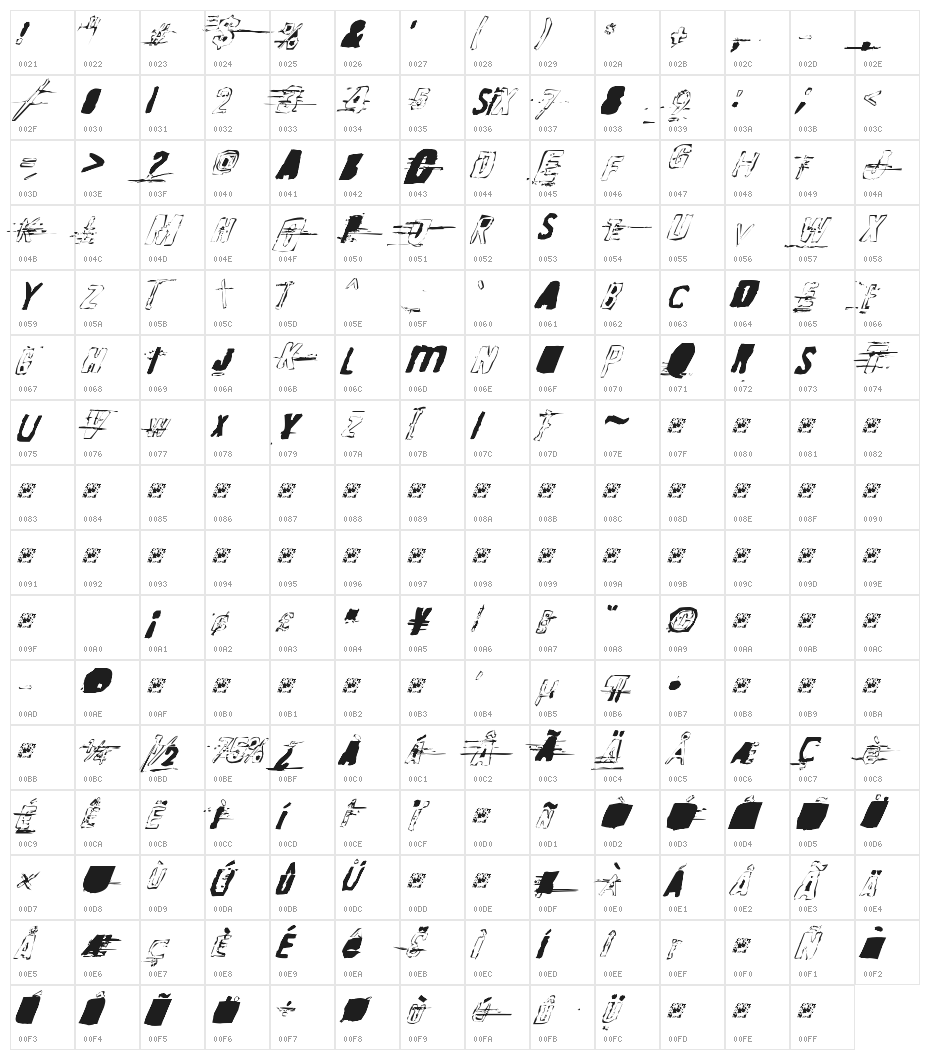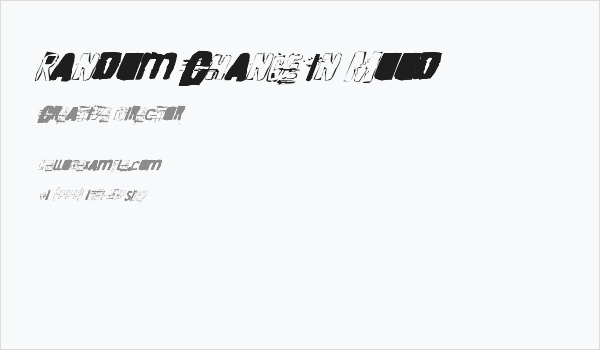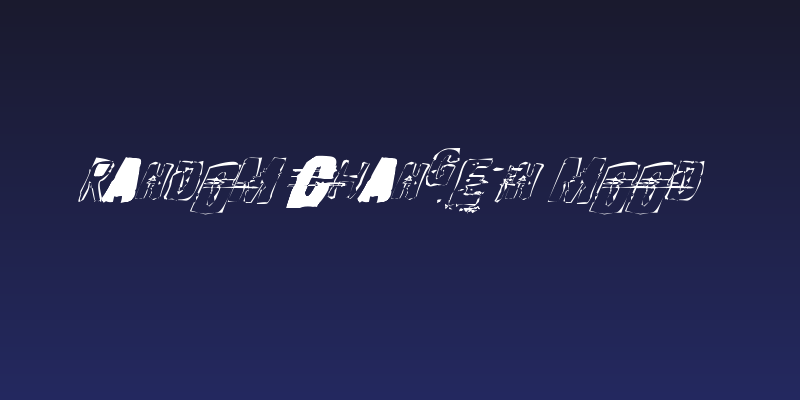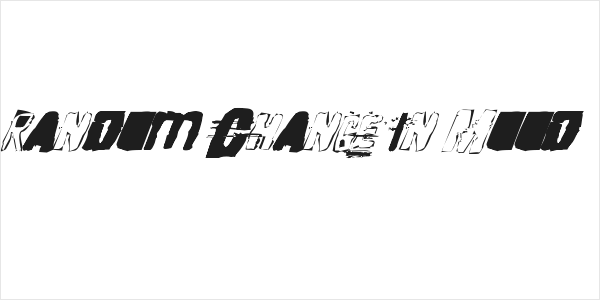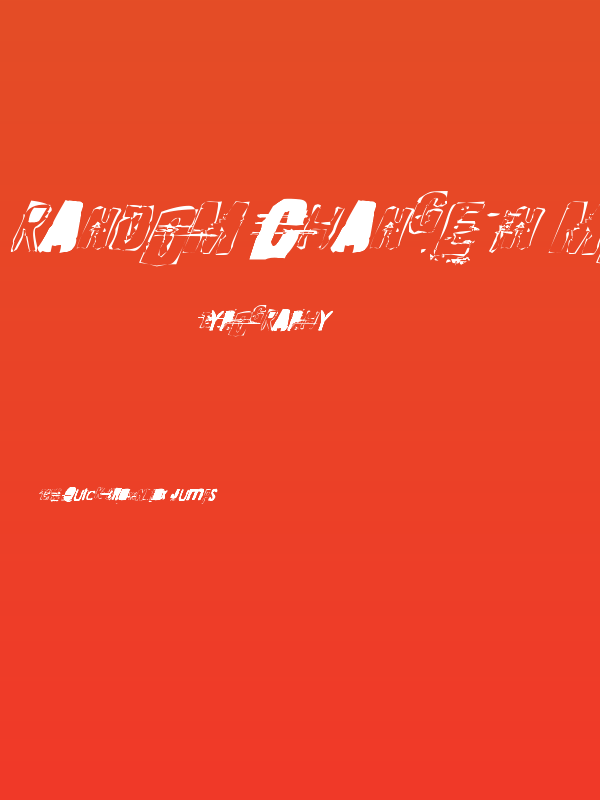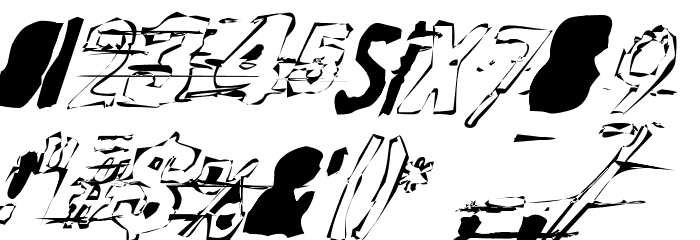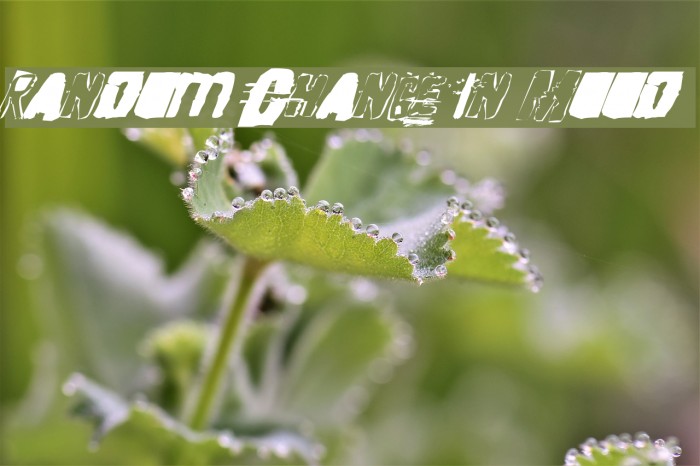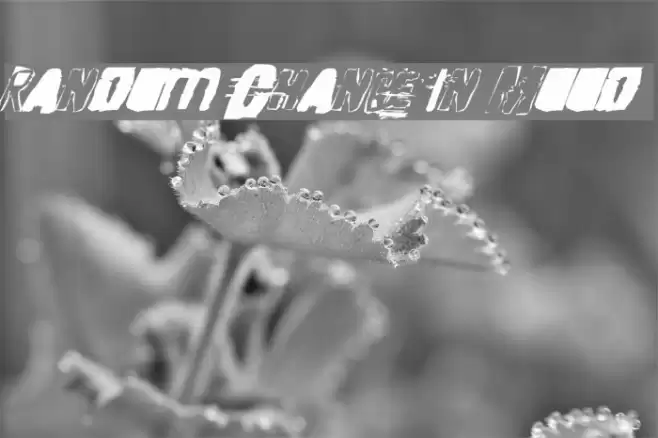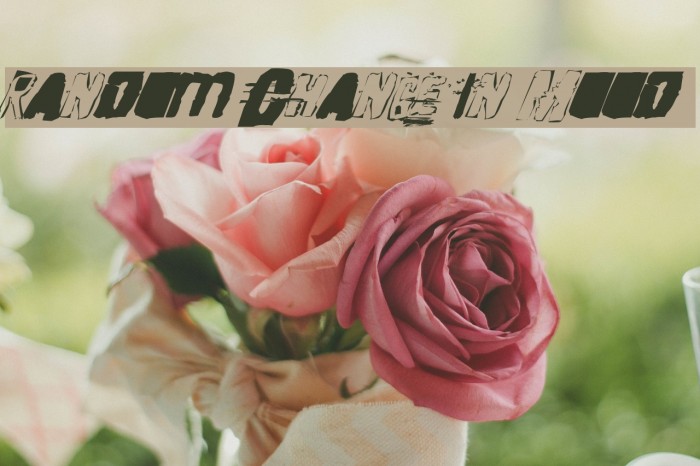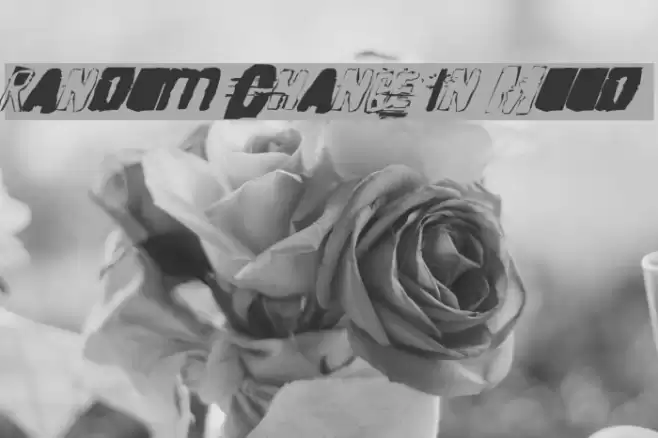
Random Change in Mood Font
✎ Distorted Eroded
| Projetos propostos | Ideal for projects that require a bold statement, such as album covers, posters, or branding for edgy and modern products. |